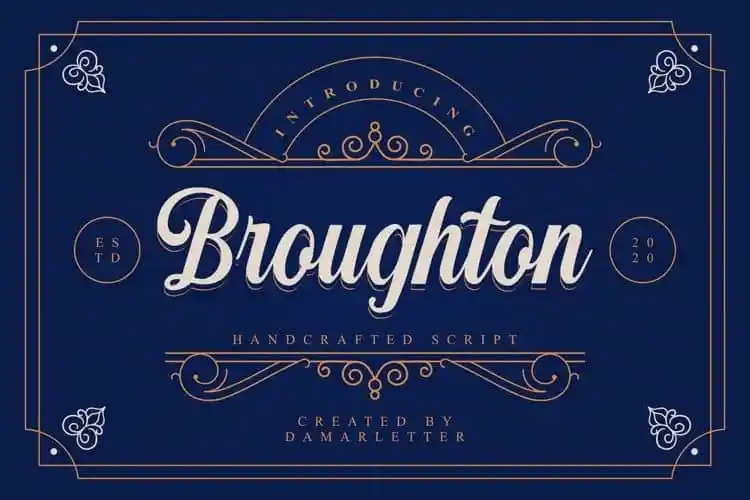
Broughton Script Font – Download Grátis
A Broughton Script Font é uma criação inspirada no estilo Vintage e Retro, com um toque atraente do design tradicional americano. Este script elegante e sofisticado adquire um ar de luxo e estilo, tornando-o perfeito para ambientes que buscam incorporar elementos antigos numa atmosfera moderna e contemporânea. Ideal para aplicação em logotipos ou design editorial, essa fonte traz uma atmosfera retrô com um toque moderno, criando designs atraentes sem deixar de lado o encanto das antigas tipografias. Com uma sensação clássica e elegante que se torna irresistível em qualquer projeto gráfico que desejasse incorporar elementos de design tradicional americano ao modernismo atual.